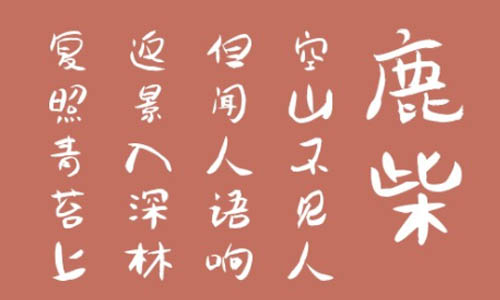
南構(gòu)金申中卡通字體是一款非??蓯?ài)的卡通字體,是由金申中老師創(chuàng)作的藝術(shù)字體,整個(gè)字體圓潤(rùn)飽滿(mǎn),俏皮可愛(ài),結(jié)構(gòu)嚴(yán)謹(jǐn),在字形的創(chuàng)新上獨(dú)樹(shù)一枝,南構(gòu)金申中卡通主要用于學(xué)校,幼兒園,兒童游樂(lè)場(chǎng),兒童寫(xiě)真館,兒童藝術(shù)培訓(xùn),兒童服飾,兒童食品等與兒童相關(guān)的領(lǐng)域,也可用于非主流,咖啡屋等門(mén)牌設(shè)計(jì)。歡迎大家前來(lái)下載。